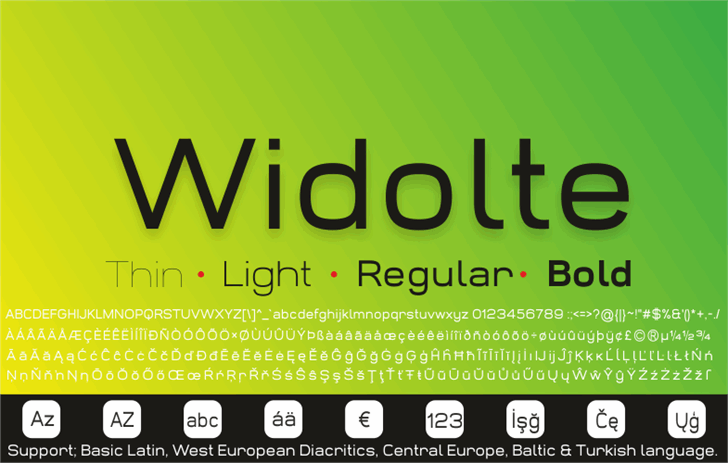
Esta é uma pequena demo do caráter disponível para a Font ‘Widolte Bold’. Para quem está interessado no uso comercial desta fonte, a Studiotypo.com oferece mais detalhes sobre como usá-la. Visite a página www.studiotypo.com/widolte_testscreen e fique por dentro de todas as especificações necessárias para o seu projeto empresarial. ‘Widolte Bold’ é uma escolha ótima para quem procura fontes sans-serif que se destacam pela sua simplicidade e elegância, adequadas a qualquer tipo de design gráfico. Aqui na Studiotypo.com, acreditamos em oferecer ferramentas de alta qualidade sem comprometer a nossa responsabilidade ética. Se você está procurando por mais opções de fontes para seu próximo projeto de design, essa é uma excelente fonte para considerar.
Designer: Studiotypo